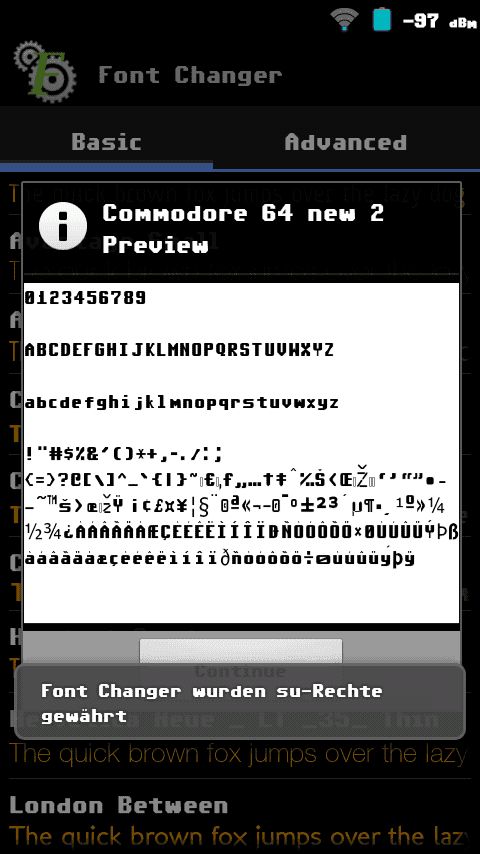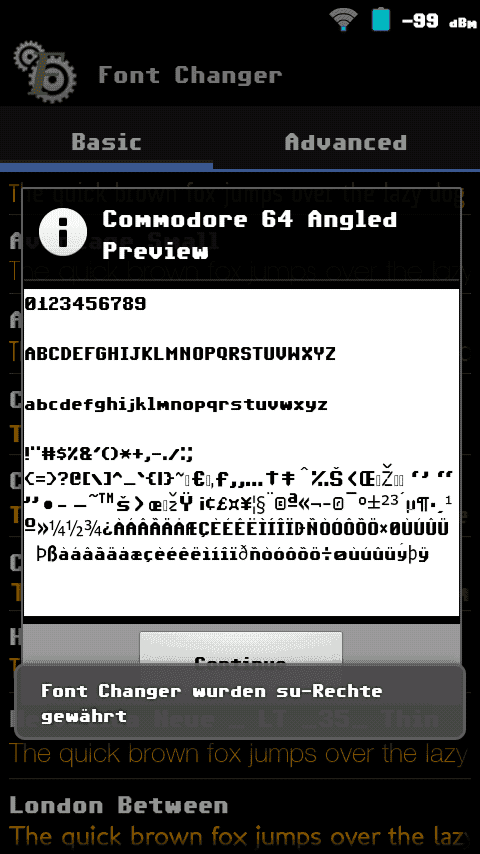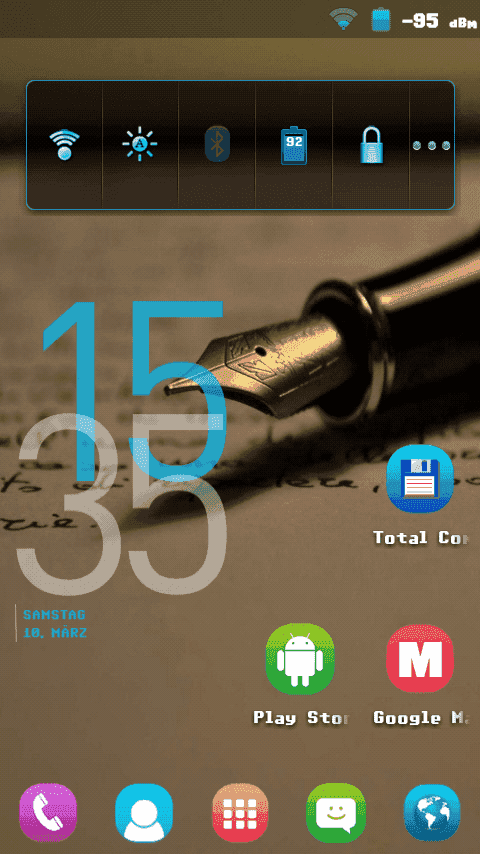
im Anhang die c64 Schrift in 2 leicht verschiedenen Versionen (falls den noch wer kennt) mit ß und Ä's,Ö's,Ü's & vielen weiteren Sonderzeichen (Hab keine mit ß finden können, darum hab ichs von ner anderen Schrift kopiert und versucht anzupassen).